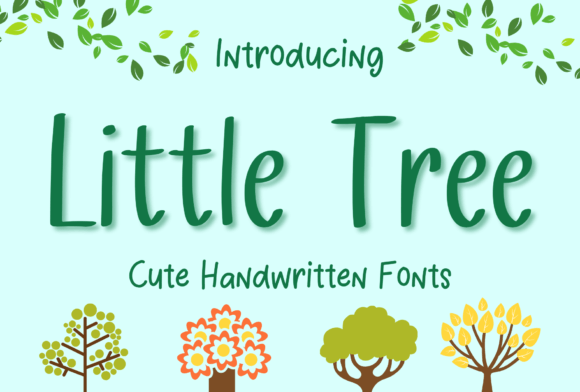
Little Tree
適切なデザイン要素を見つけるのは難しい場合がありますが、Little Treeは作品を即座に引き立てる優れたコレクションを提供します。
精密に作られたLittle Treeは、クリーンなベクター、滑らかなタイポグラフィ、そして安心のための商用ライセンスを提供します。
POD(オンデマンド印刷)製品、結婚式の招待状、またはソーシャルメディアのグラフィックを作成している場合でも、Little Treeは理想的です。